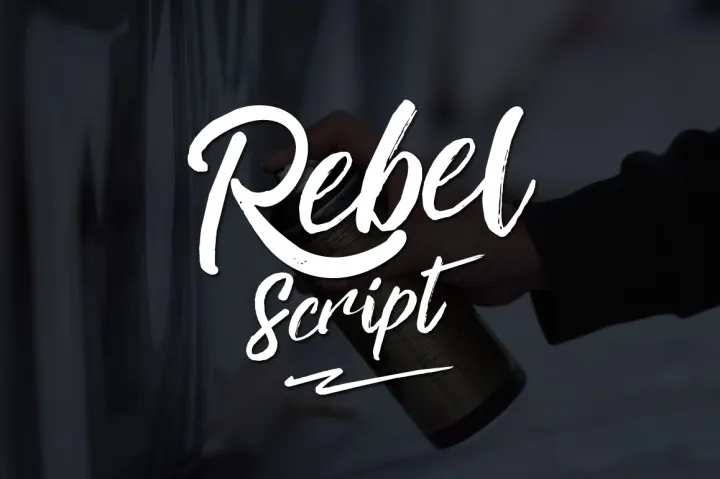
A Rebel Script Font é uma elegante fonte brush que combina graça e força no seu design elegante. Desenvolvida pelo designer Hamilton, ela se destaca nas categorias de fóruns de texto e gráficos digitais. Estamos super entusiasmados em anunciar que esta linda fonte está agora disponível gratuitamente na TheHungryJPEG, uma plataforma repleta de recursos estilosos para designers amadores e profissionais. É importante destacar que este oferecimento é temporário: você terá apenas 14 dias para garantir a sua download gratuita antes do preço retornar ao seu nível normal. Essa fonte traz elementos únicos e intrigantes, perfeitamente adaptados para criar uma identidade visual diferenciada em seus projetos. Ela é ideal tanto para design de websites quanto para uso em logotipos ou artes digitais mais elaboradas. Independentemente do seu projeto, a Rebel Script Font certamente enriquecerá sua ferramenta de design e será um dos elementos-chave que tornará seu trabalho único e imprimível.